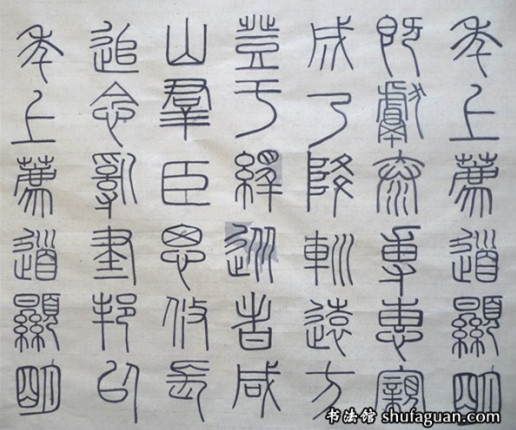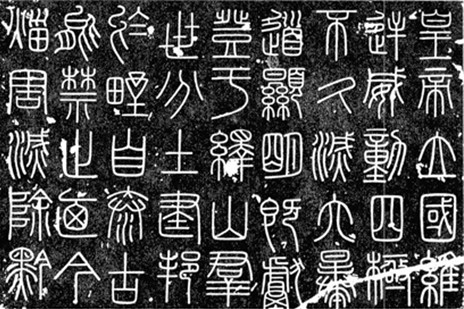
李斯书法_书法鼻祖_李斯书法作品欣赏_李斯书法价值地位
李斯,秦代著名的政治家、文学家和书法家。李斯的文学和文字的造诣令后人追捧。他的文章论证严密、气势贯通,洋洋洒洒,如江河奔流,鲁迅曾经大力称赞李斯,被称为书法鼻祖。
李斯书法鼻祖作品
李斯和赵高、胡毋敬等人写了《仓颉篇》、《爰历篇》 和《博学篇》等范本,供大家临摹。
李斯书法作品欣赏
李斯书写的刻石有《泰山封山刻石》、《琅琊刻石》和《峄山刻石》等。